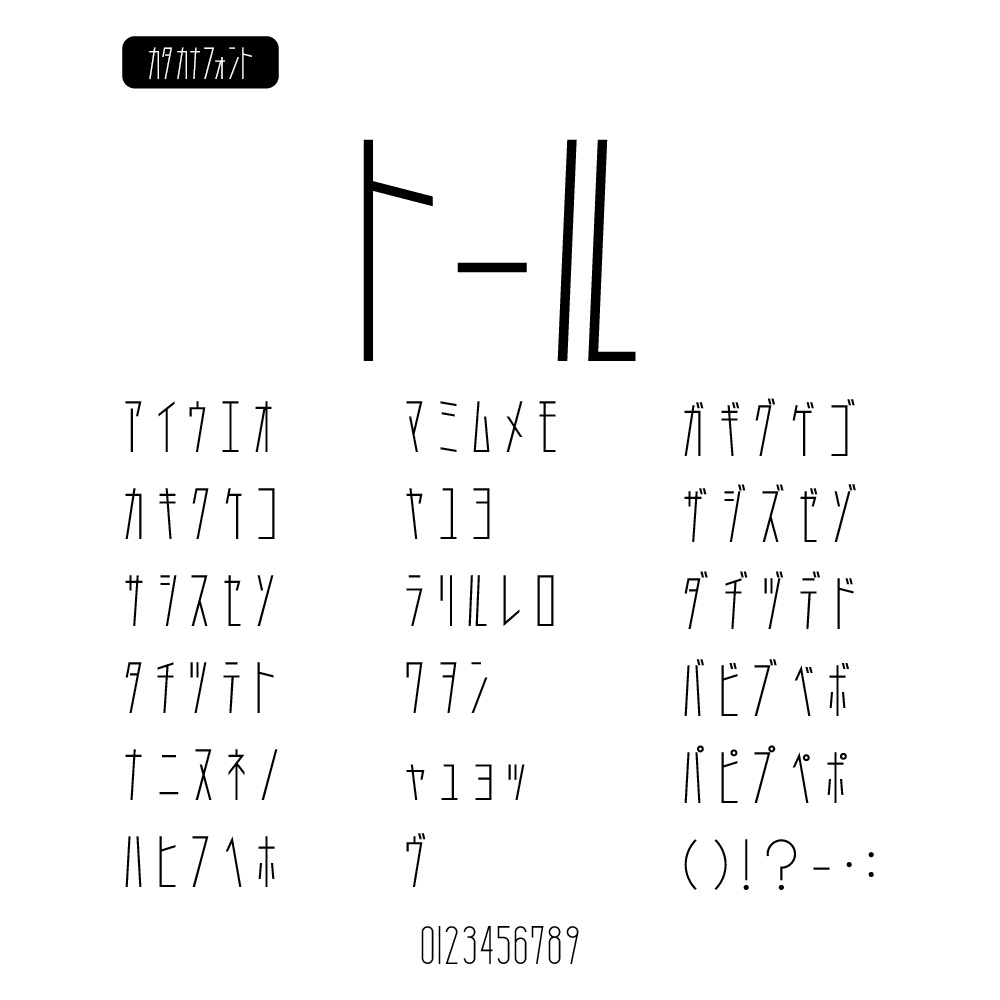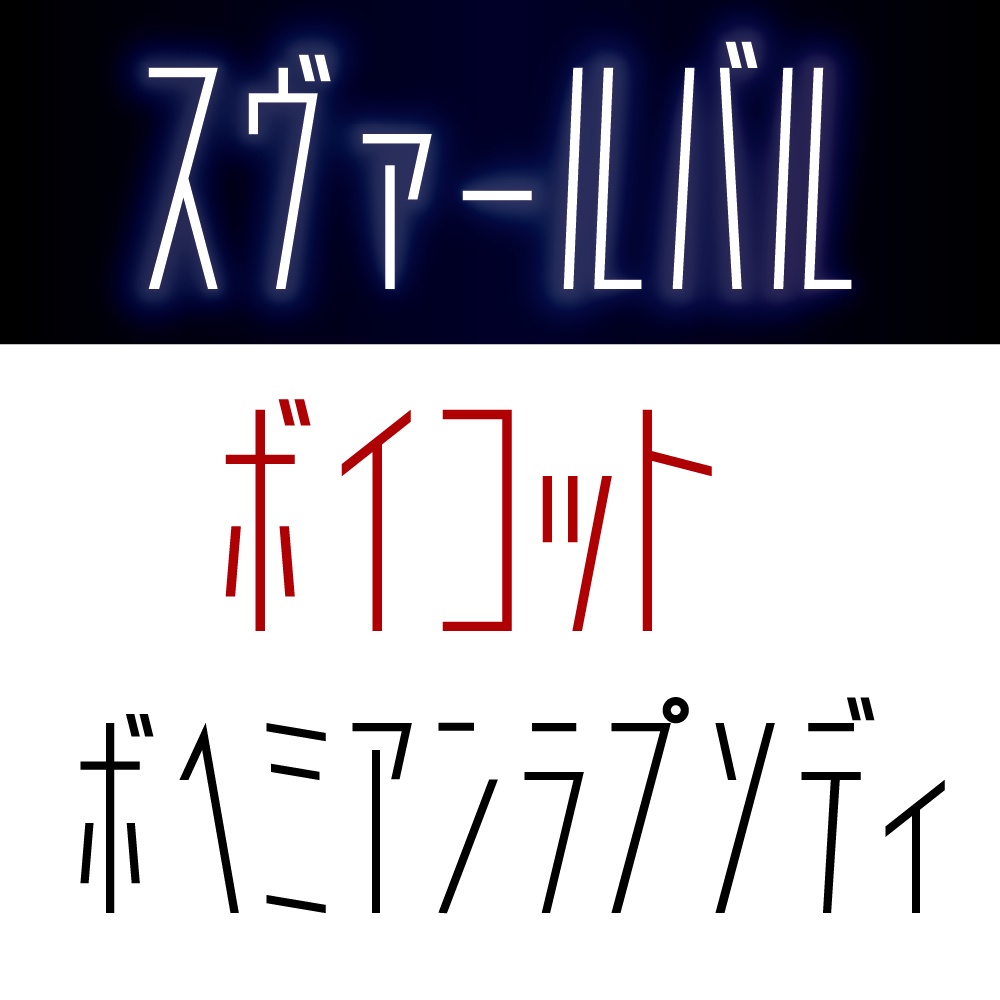
トール(カタカナ専用フォント)
【概要】 極細で繊細なデザインが特徴の、カタカナ専用フォントです。 幾何学的で整った構造が、モダンでスタイリッシュな印象を与えます。 SF・近未来系、ファッション・ブランド系など、洗練されたデザインに最適です。 【収録文字】 ・全角カタカナ ・欧文数字 0〜9 ・一部記号(ー()!?・ など、基本的な記号のみ) 【想定用途】 ・SF・近未来系のタイトル、ロゴ ・ファッション・ブランド系デザイン ・ミニマル・モダン系の Web サイト見出し ・映画・ゲームのタイトル画面 ・高級感のあるパッケージデザイン ・SNS 用画像 など 【対応環境】 ・フォント形式:OpenType フォント(.otf) ・動作確認済み:Windows 10 / Windows 11(日本語版) ・上記以外の OS(macOS など)や一部アプリケーションでもご利用いただける場合がありますが、 作者は動作保証・サポートを行っておりません。 【カーニングについて】 ・カタカナ向けのカーニング情報を含んでいます。 ・Adobe Illustrator / InDesign などの DTP ソフトでは、文字パネルの「カーニング」を「メトリクス」に設定してお使いください。 ・Web フォントとして利用することも可能ですが、カーニングの反映状況はブラウザや環境に依存します。 環境によってはカーニングが反映されない場合があります。 【ライセンス/利用範囲(有料版)】 ・個人・商用利用どちらも可能です。 ・本フォントを使用して作成したロゴ、画像、動画、印刷物などの成果物は、自由に配布・販売していただけます。 ・ただし、本フォントを使用して作成したロゴ・マーク等を商標登録・意匠登録することはできません。 ・フォントファイル自体の再配布・再販売、フォントデータを改変して別フォントとして再配布する行為は禁止です。 ・1 ライセンスにつき、ユーザーが所有または管理する 2 台までの PC でご利用いただけます(同時使用は同一ユーザーに限ります)。 ・詳しい条件は同梱の「EULA.txt」を必ずご確認ください。 【ファイル内容】 ・Kirigamine.otf ・EULA.txt(利用規約) ・README.txt(概要と注意事項) 【注意事項】 ・本フォントおよび本フォントを用いて生成した画像・アウトラインデータを、機械学習・AI モデルの学習データとして使用することを禁止します。 ・フォントの表示結果やカーニングは、OS やアプリケーション、ブラウザ、描画エンジンの違いにより異なる場合があります。 必要に応じて文字間や行間を調整してご利用ください